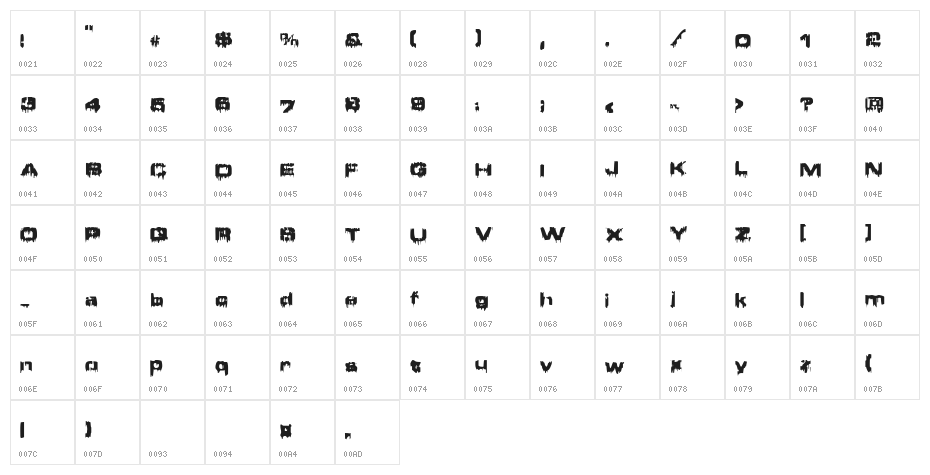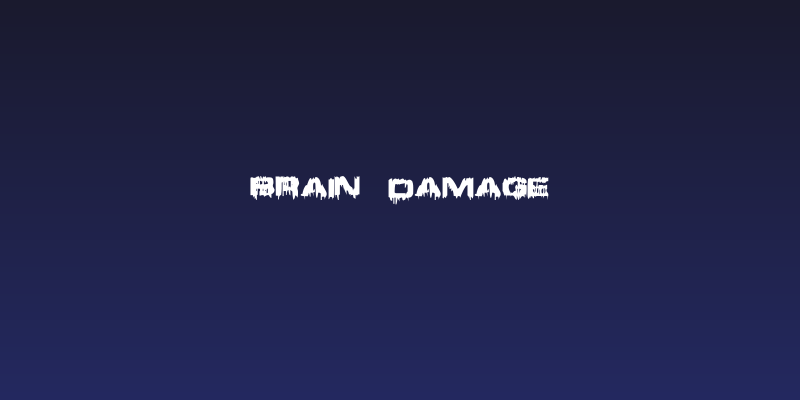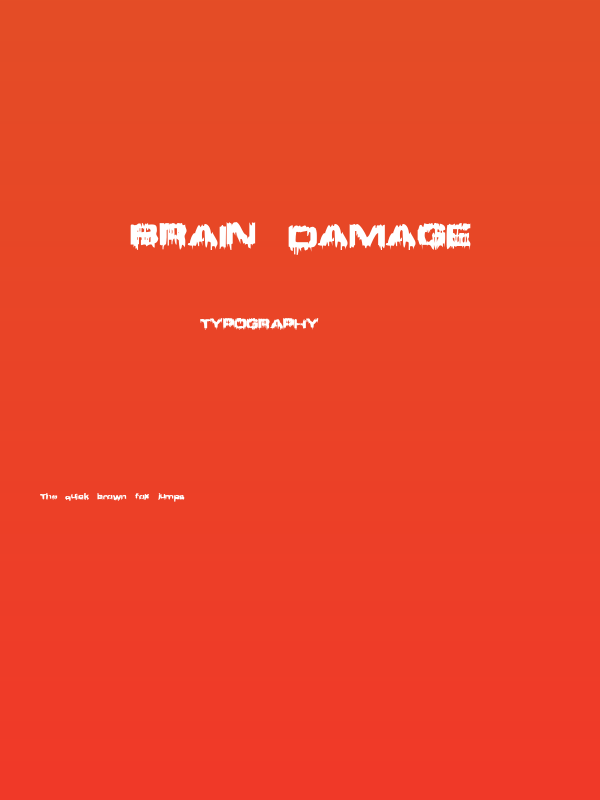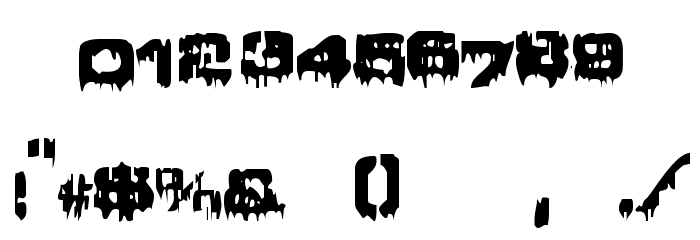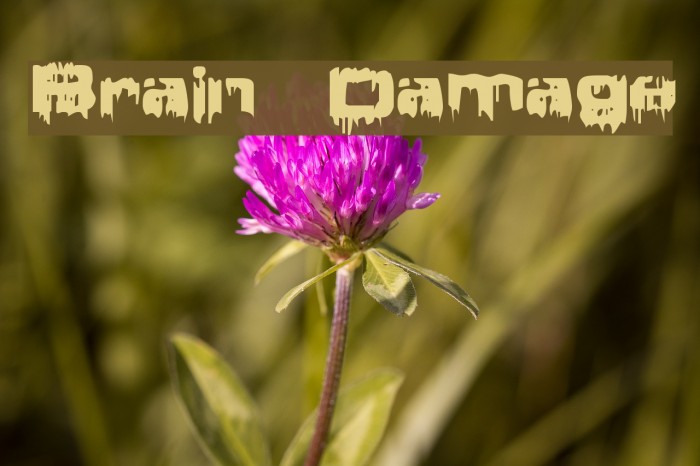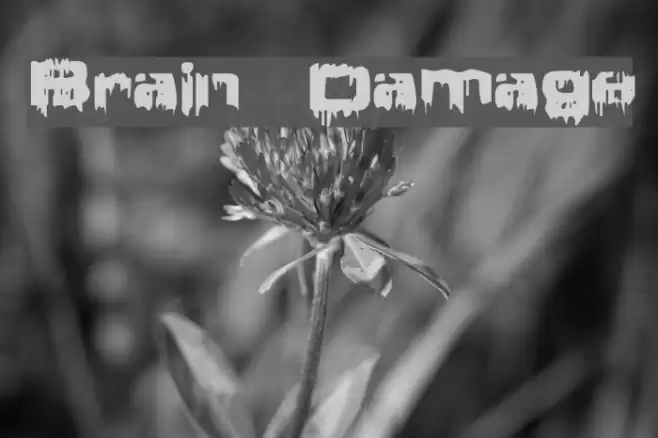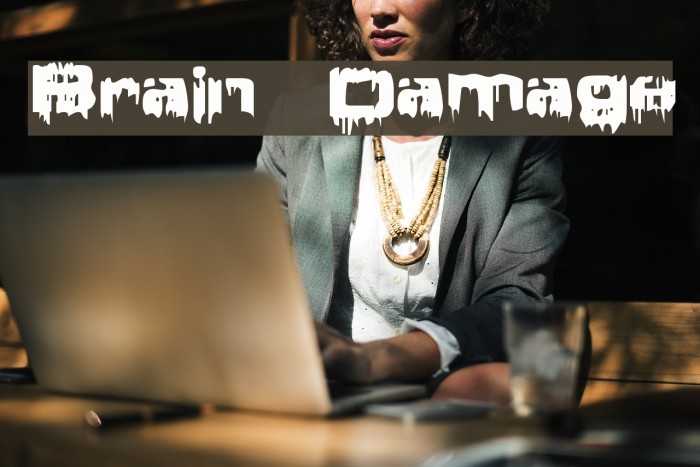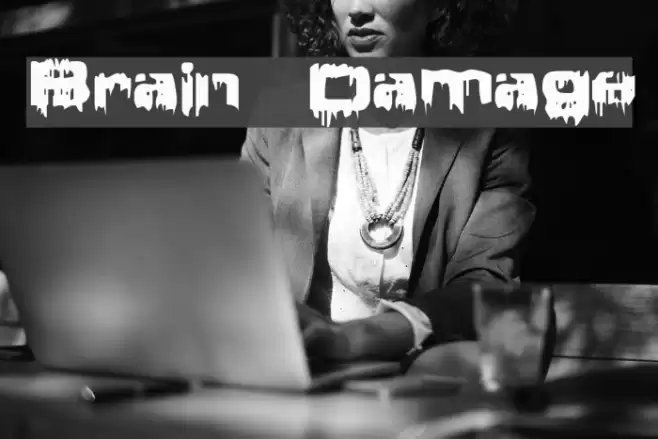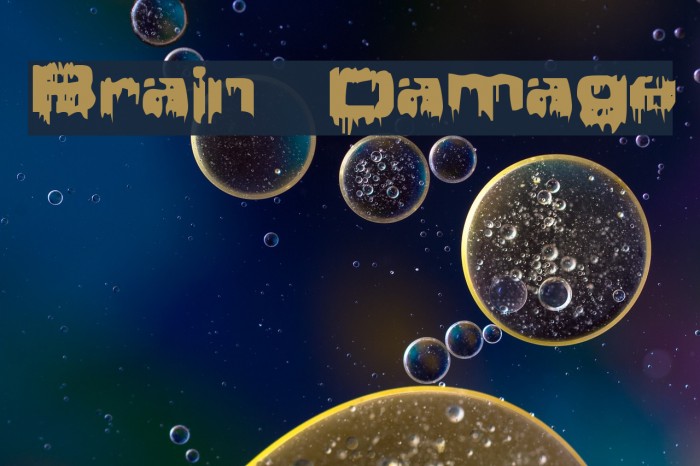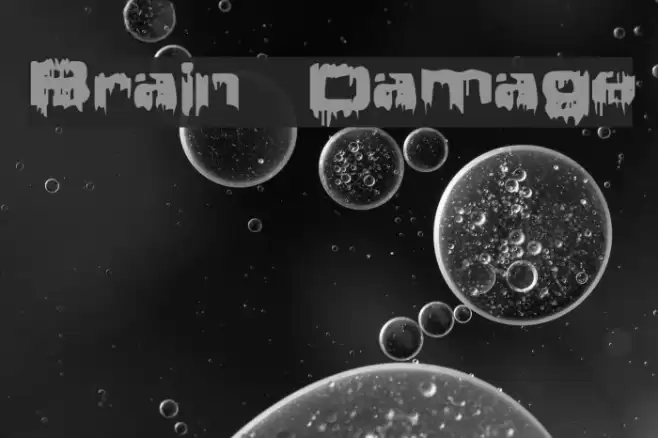
Brain Damage Font
| おすすめプロジェクト | Ideal for horror movie posters, punk band album covers, Halloween event flyers, or any project needing a dramatic, edgy look. |